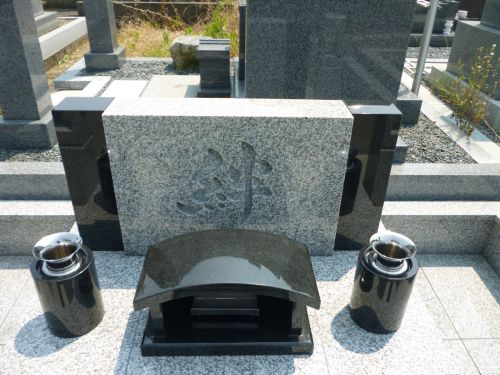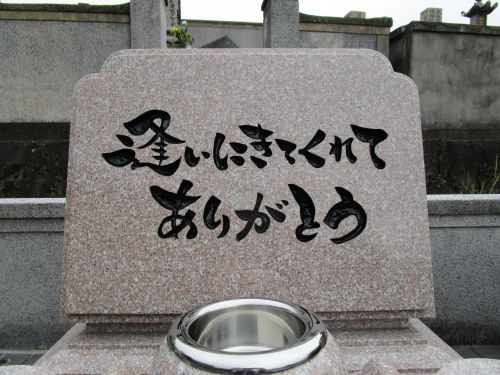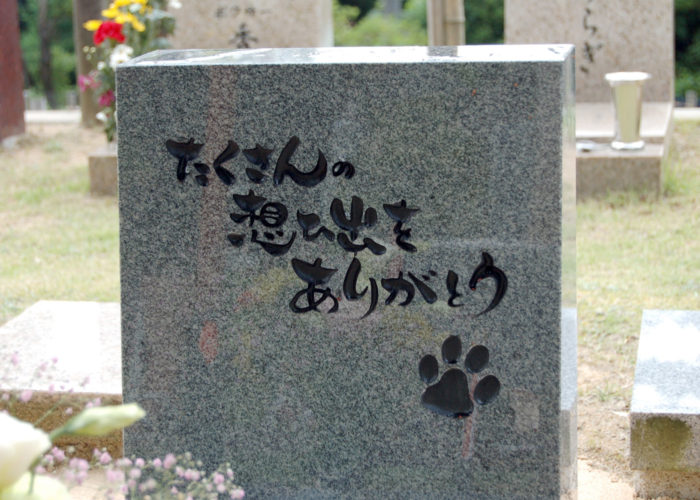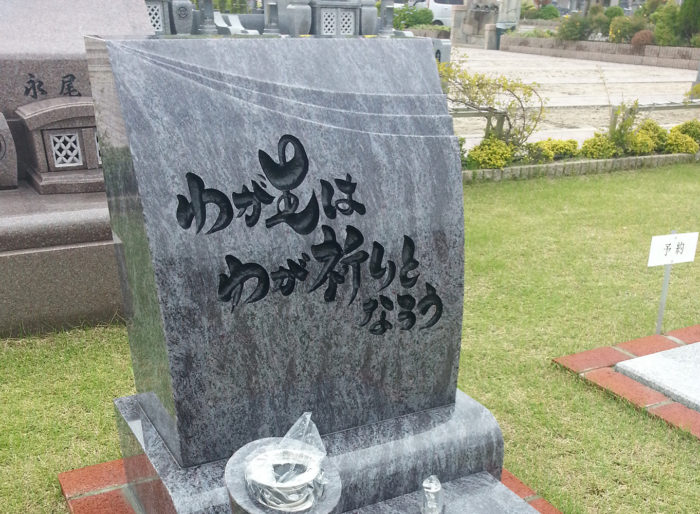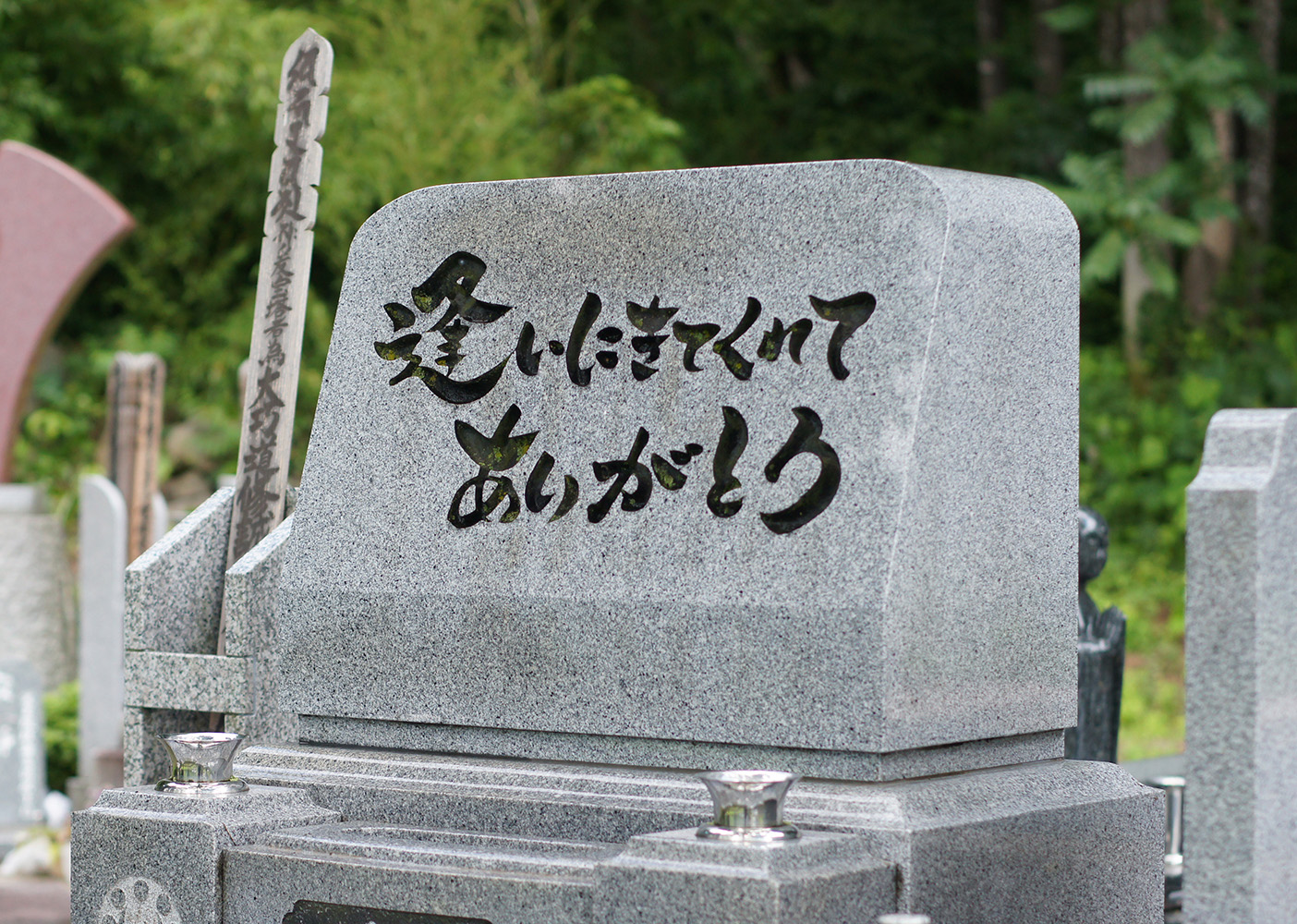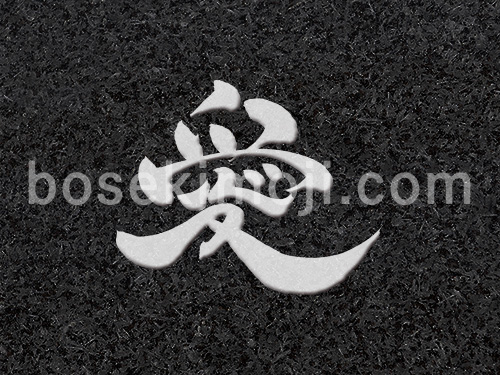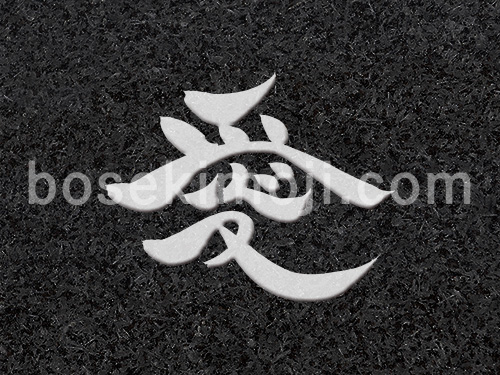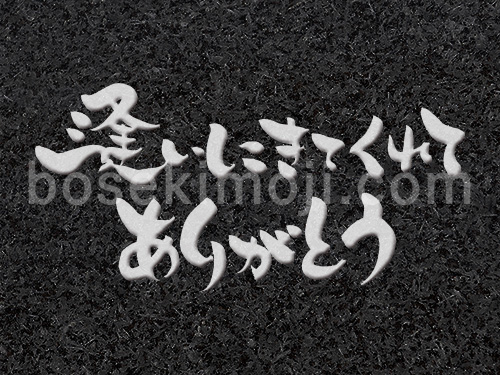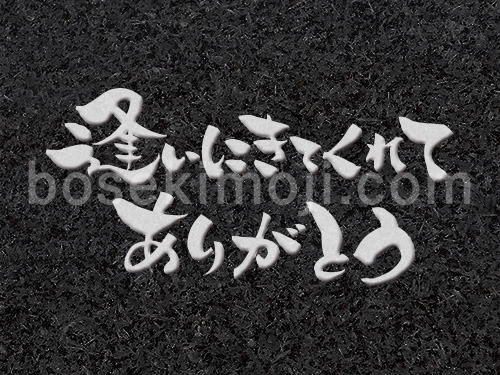
供養の心で書く
墓石文字
墓石文字.comは、僧侶が書くあたたかな筆文字による、墓石文字サービスです。故人や家族の想いを込めた言葉や家名を、美しいオリジナル書体で仕上げます。
書の作品集からお選びいただくプラン、ご希望の言葉や家名を筆文字で書き下ろした中からお選びいただくプランなど、ご家族の様々な想いに寄り添ったお墓をご提案いたします。
墓石文字:逢いに来てくれてありがとう
墓石文字作品集より
●林映寿和尚が筆文字で書いた、24種の書からお選びいただけます。
墓石文字:和楽
墓石文字作品集より+家名
●お墓の文字は、作品集に掲載の24種の書からお選びいただけます。
●家名は、林映寿和尚が書き下ろした3点の書の中からお選びいただけます。
墓石文字:道
オリジナル墓石文字
ご希望の言葉、または家名
●林映寿和尚が書き下ろした3点の書の中からお選びいただけます。(書の修正は無料)
墓石文字作品集